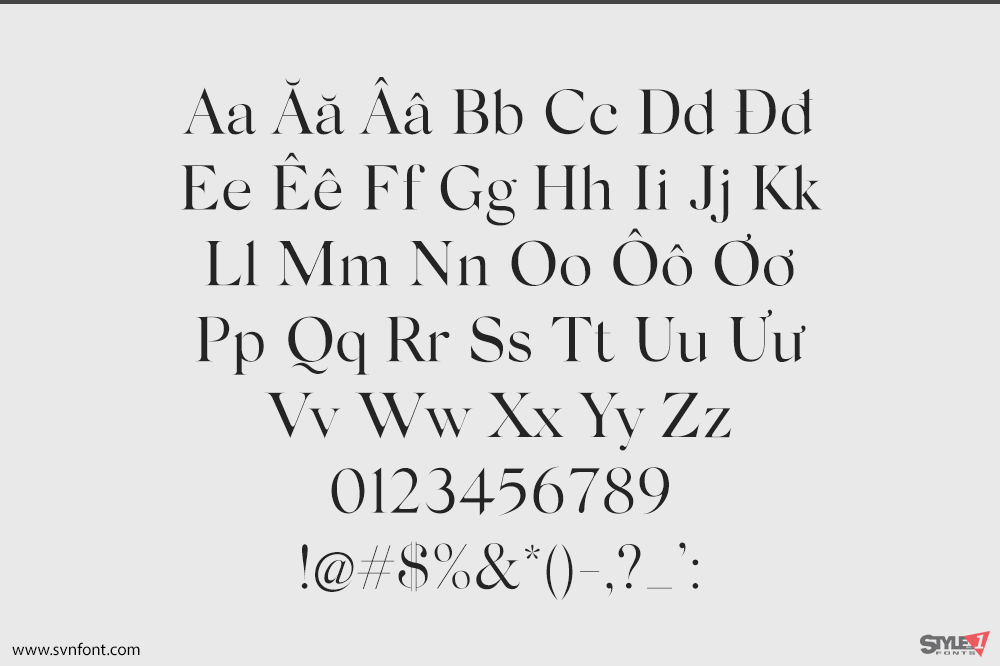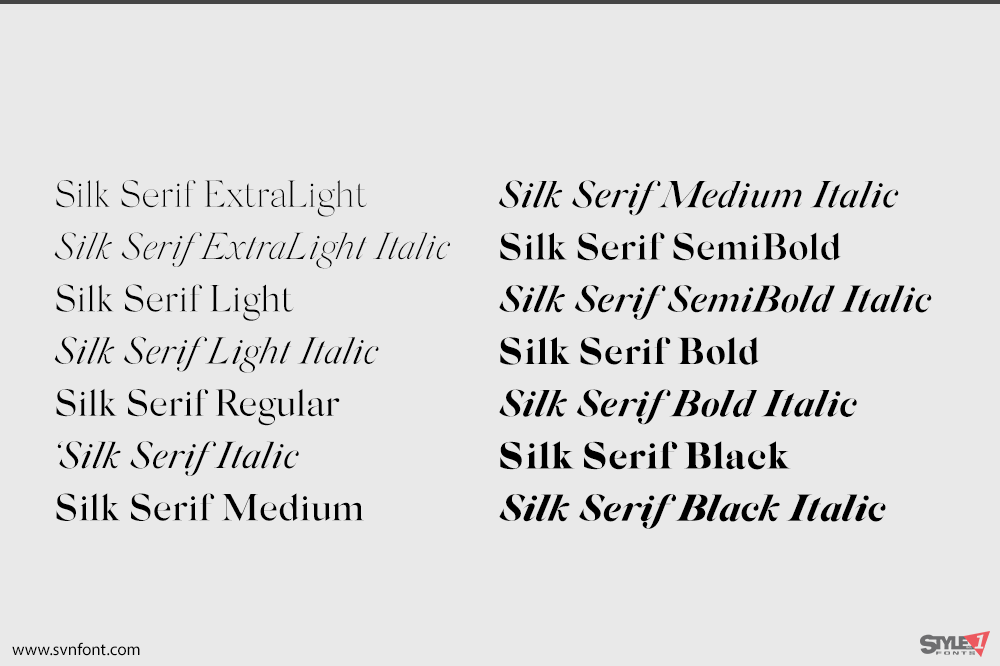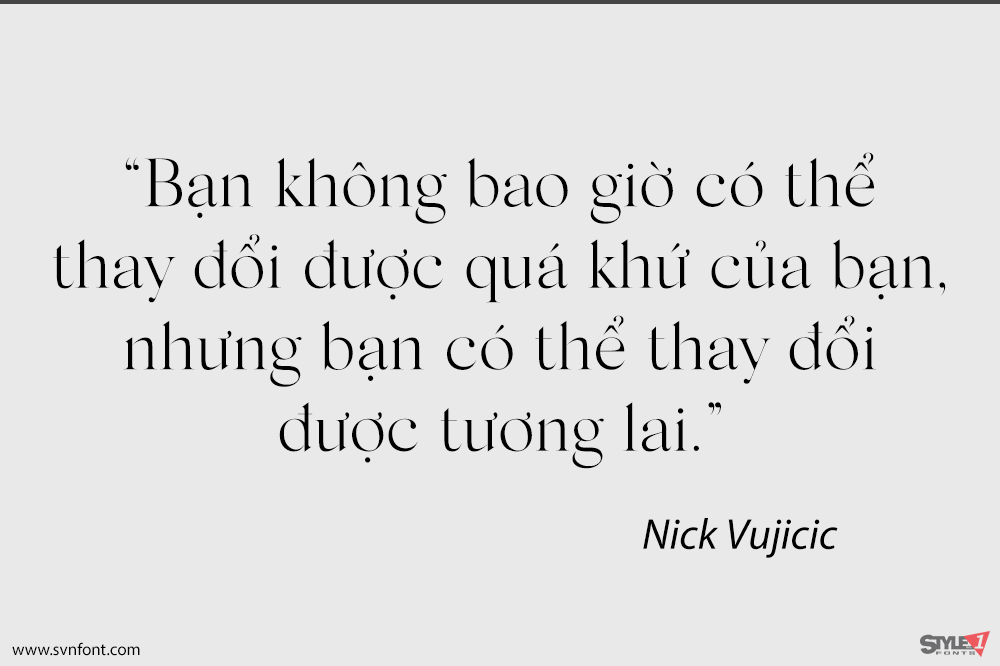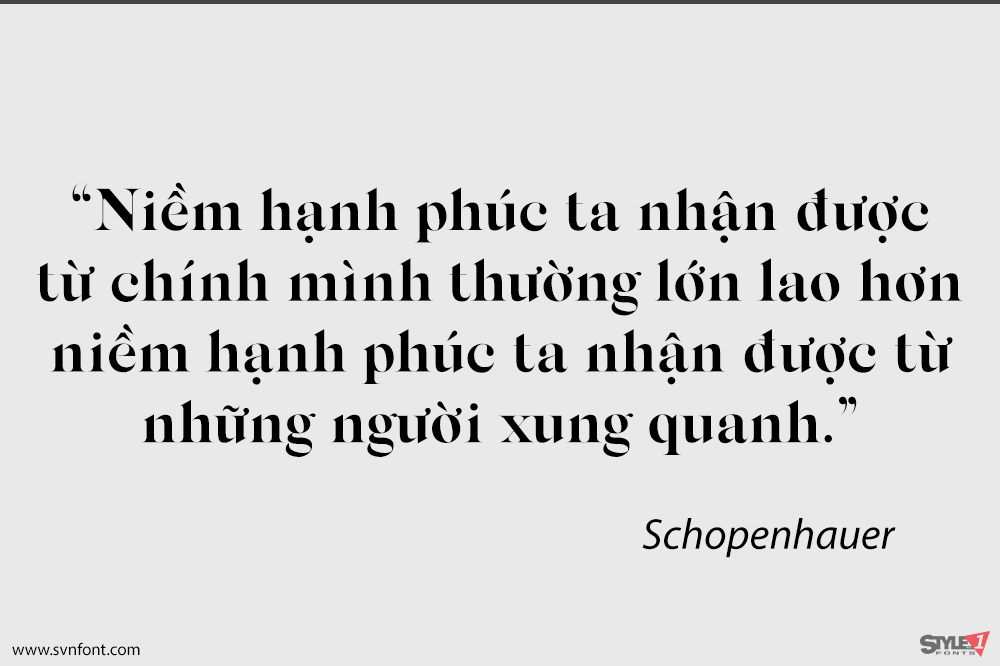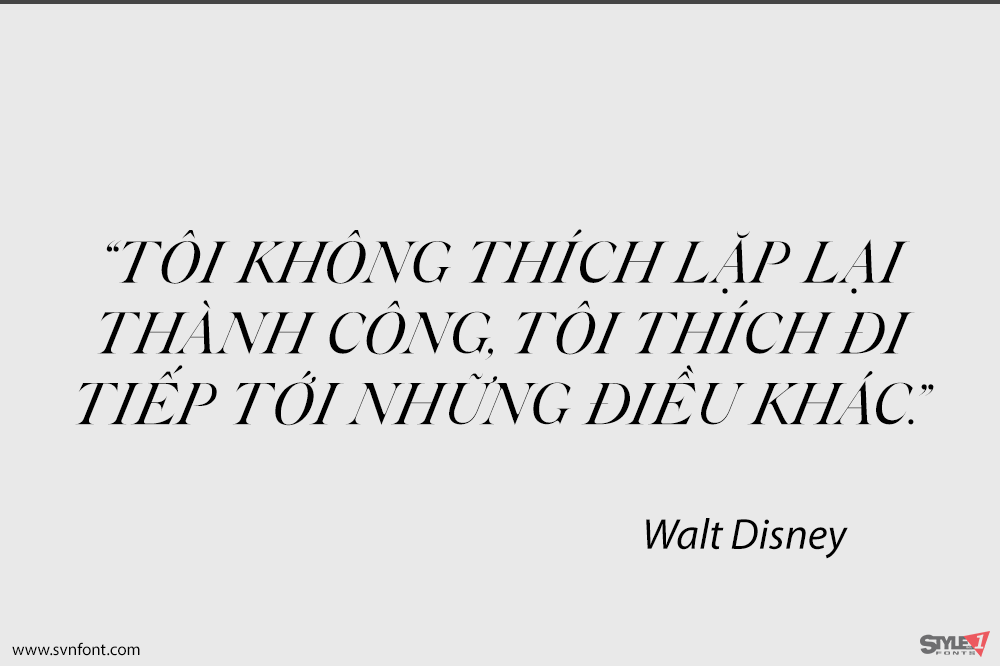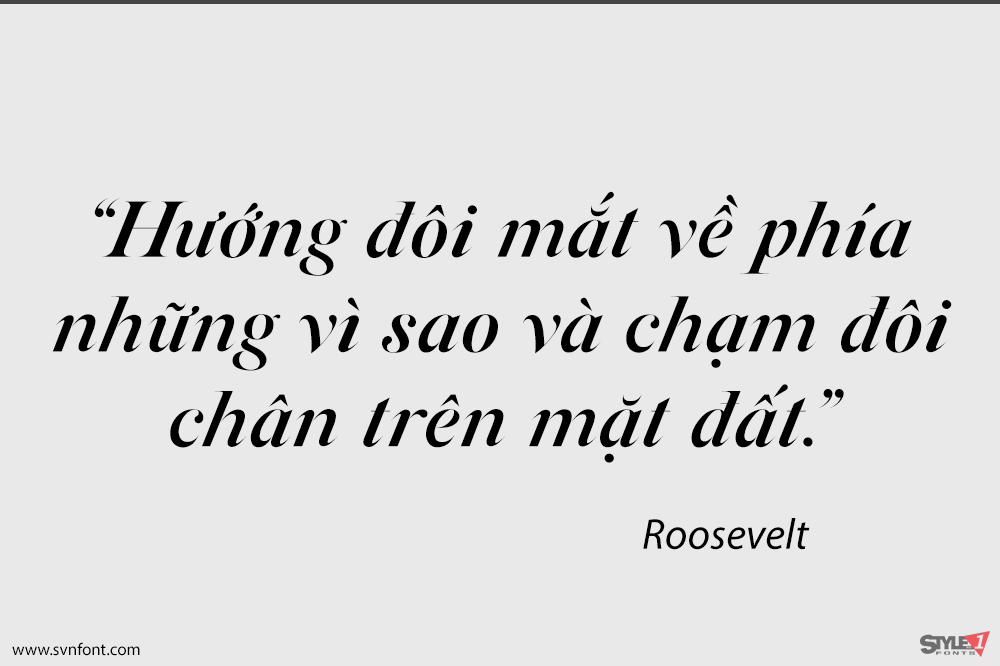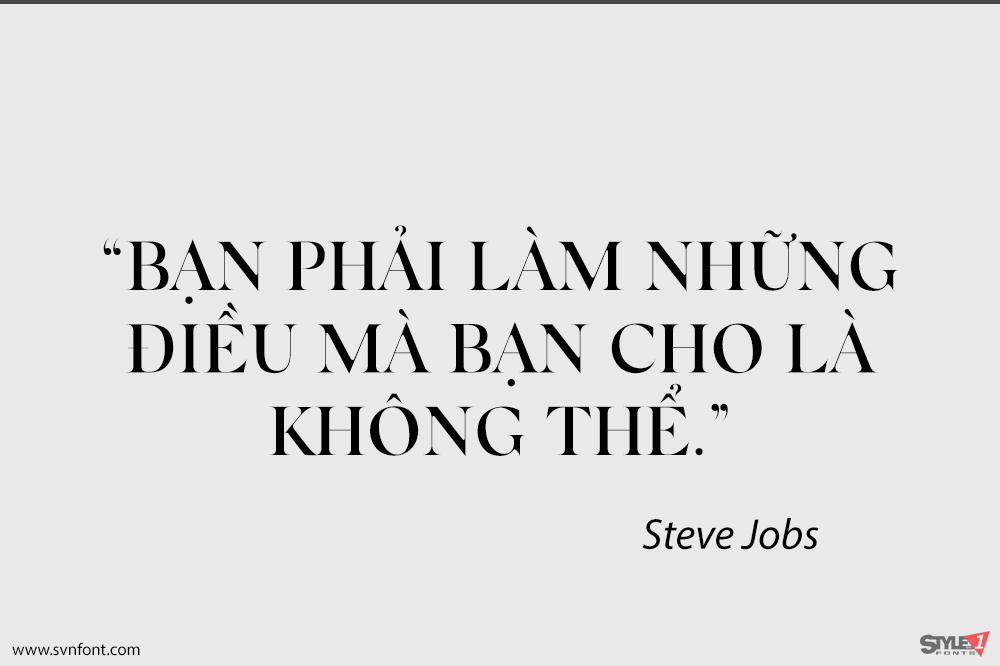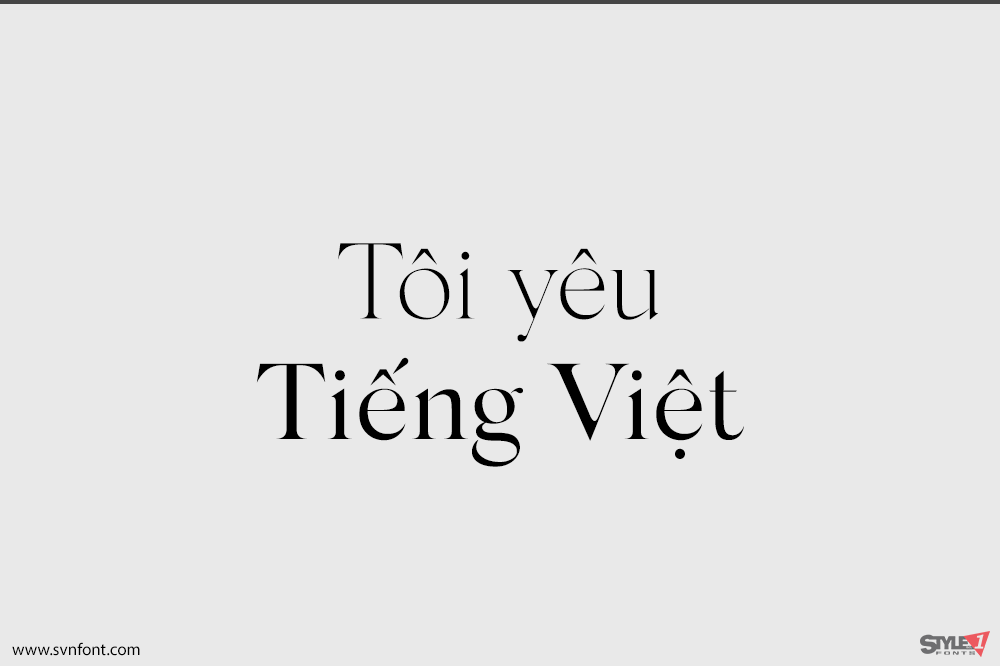
Silk Serif là một kiểu chữ có độ tương phản cao, với các nét serif mỏng, nhọn, có chân nối rõ ràng và các đầu tròn (ball terminal) ở những vị trí thích hợp, cùng với các điểm nối có chân trong nhiều hình dạng chữ. Đặc điểm chính của kiểu chữ này là sự ngắt quãng giữa các nét cong (bowls) và nét thẳng (stems). Tuy nhiên, các nét cong được đặt rất gần nét thẳng, tạo ra ảo giác về sự kết nối. Silk là một kiểu chữ tinh tế và dễ đọc, nhưng trên hết, nó mang một vẻ sang trọng.
Nhà thiết kế: Rakel Tómasdóttir
Nhà phát hành: SilkType